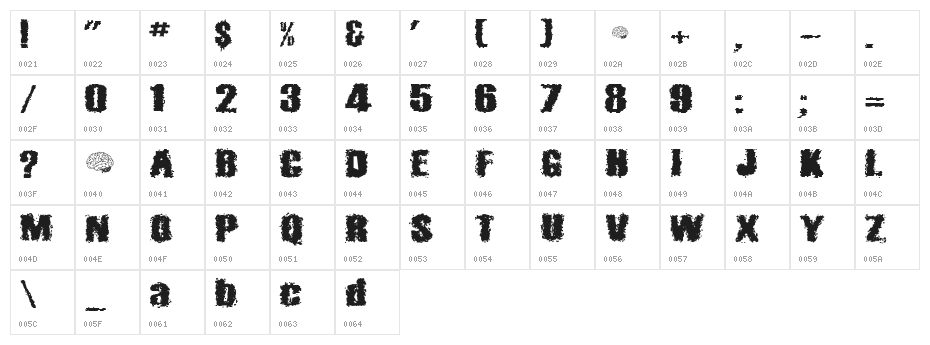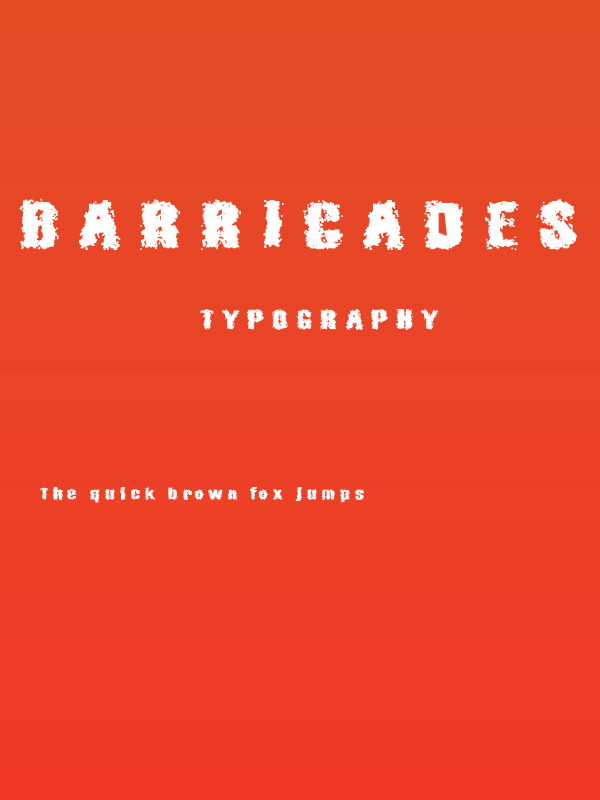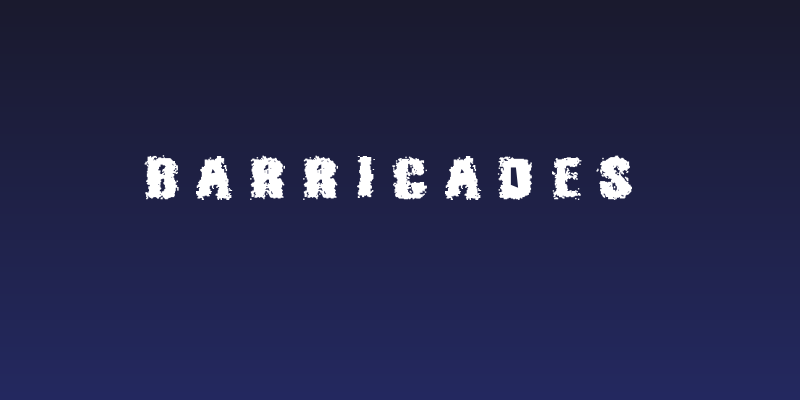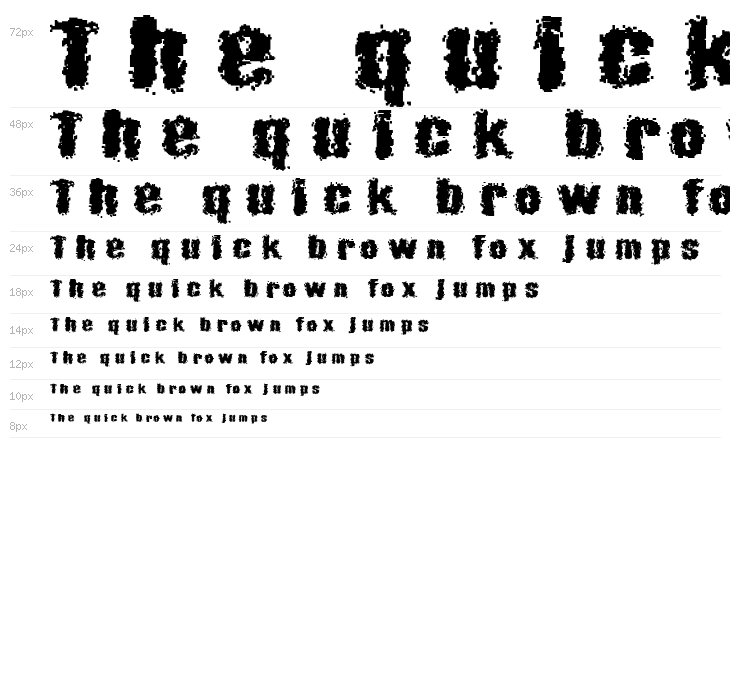
Barricades Font
| Kategorien | Decorative |
| Gesamtstil | Grunge, Edgy |
| Vorgeschlagene Projekte | Ideal for album covers, posters, urban-themed designs, and branding that requires a bold, edgy look. |